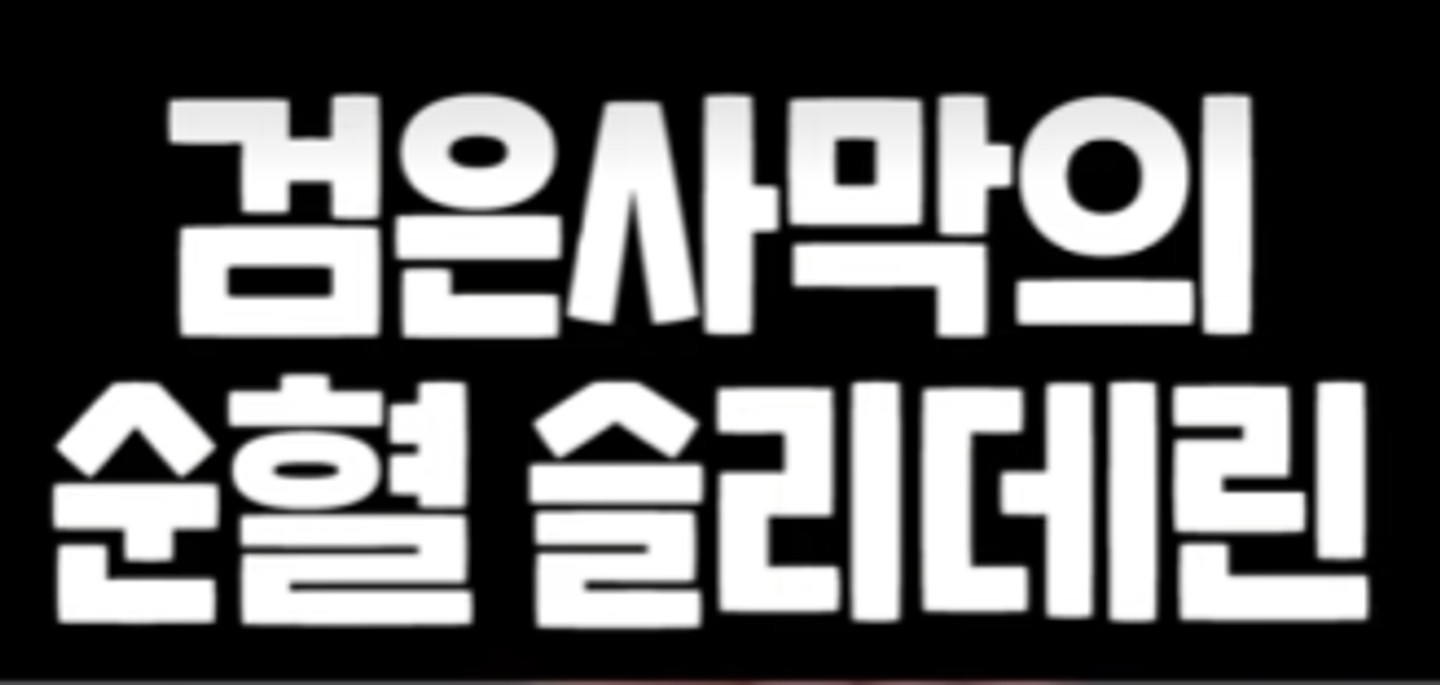
Sandoll 호요요체
산돌 호요요는 산돌에서 최초로 시도하는 가변폭 폰트입니다. 기존에 선사하지 못했던 새로운 경험을 줄 수 있는 실험적이고 유쾌한 서체를 생각하며 제작했습니다. 꽉 찬 네모꼴을 기본으로 하지만 타이핑 할 경우 예측할 수 없는 가변폭을 갖고 있으며 같은 글자를 반복 입력했을 떄도 동일한 효과가 나타납니다.
산돌호요요체